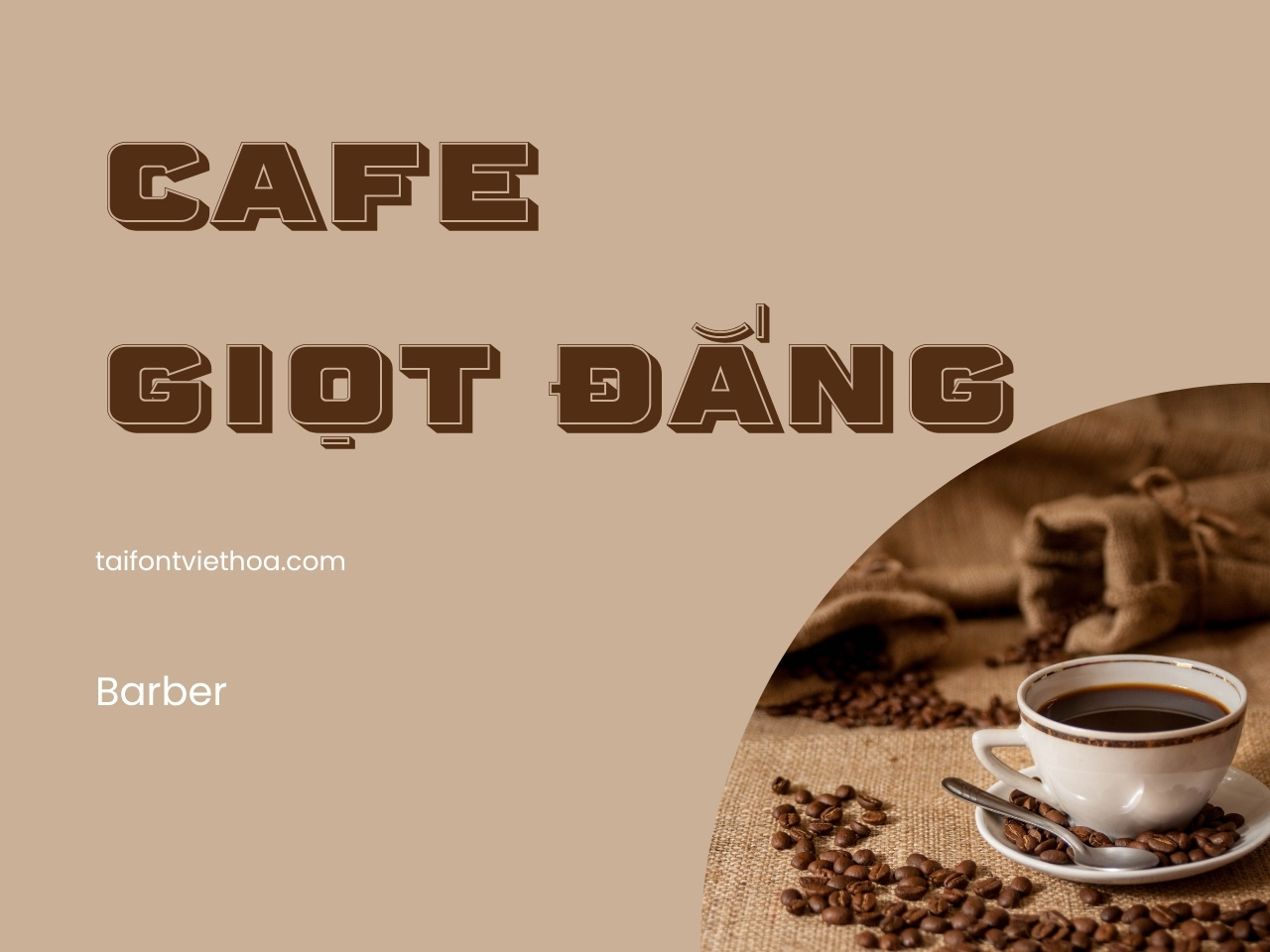
Giới thiệu về font Barber và phiên bản Việt hóa
Font Barber là một thiết kế thuộc nhóm font display, lấy cảm hứng từ bảng hiệu cổ điển tại các tiệm cắt tóc, quán barber shop và signage retro. Với phong cách đặc trưng pha trộn giữa truyền thống Mỹ thập niên 1950 và nghệ thuật typography cổ điển, Barber nhanh chóng được ưa chuộng trong các thiết kế nhận diện mang cá tính mạnh. Bộ font này được phát triển bởi studio chuyên về thiết kế signage và branding thương mại tại châu Âu, hỗ trợ hơn 60 ngôn ngữ sử dụng hệ thống ký tự Latin tiêu chuẩn.
Phiên bản Việt hóa được thực hiện bởi Hoàng Lê, với sự chăm chút trong từng chi tiết để đảm bảo sự cân đối và thẩm mỹ cho hệ thống dấu tiếng Việt. Mọi dấu thanh, ký tự đặc biệt đều được điều chỉnh phù hợp với chiều cao x-height đặc trưng của font gốc. Bộ font đã được taifontviethoa.com chọn lọc, kiểm duyệt và chia sẻ nhằm phục vụ cộng đồng thiết kế Việt trong các dự án mang phong cách cổ điển, đậm chất signage hoặc thương hiệu cá tính.
Đặc trưng thiết kế và lĩnh vực ứng dụng phù hợp
Barber sở hữu cấu trúc chữ đậm, đường nét mạnh mẽ, các đầu nét được vát nhẹ tạo cảm giác thủ công và cá tính. Với độ tương phản cao và cách bố trí hình khối gãy gọn, font này tạo điểm nhấn mạnh trong tiêu đề, poster, bảng hiệu hoặc logo. Ngoài kiểu chữ cơ bản, bộ font còn có các biến thể bold, inline và outline, giúp tăng độ linh hoạt trong trình bày thiết kế.
Font Barber phù hợp cho các ngành nghề như thiết kế barber shop, coffee shop, bao bì sản phẩm thủ công, thiết kế sự kiện retro, signage thương hiệu, logo vintage hoặc bảng hiệu mang cá tính riêng. Đặc biệt hiệu quả trong quảng cáo ngoài trời, in ấn poster, standee và các thiết kế thương hiệu theo phong cách cổ điển – mạnh mẽ.